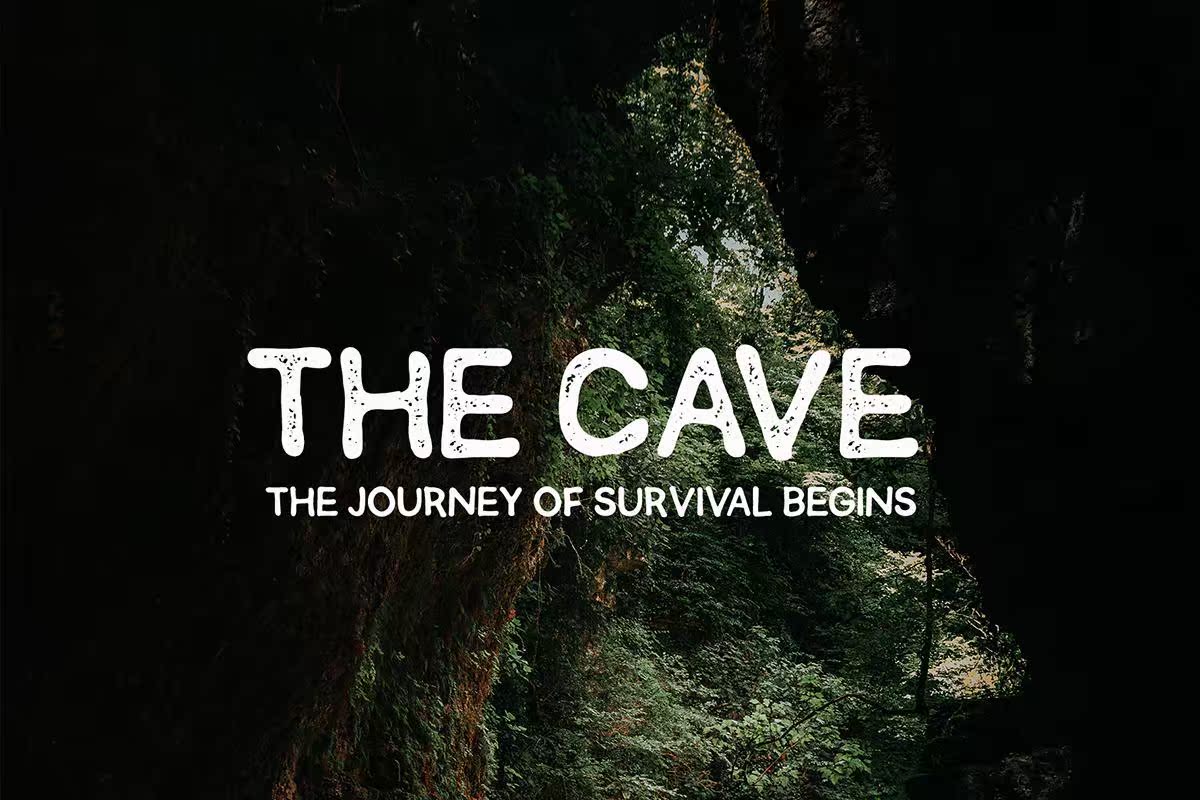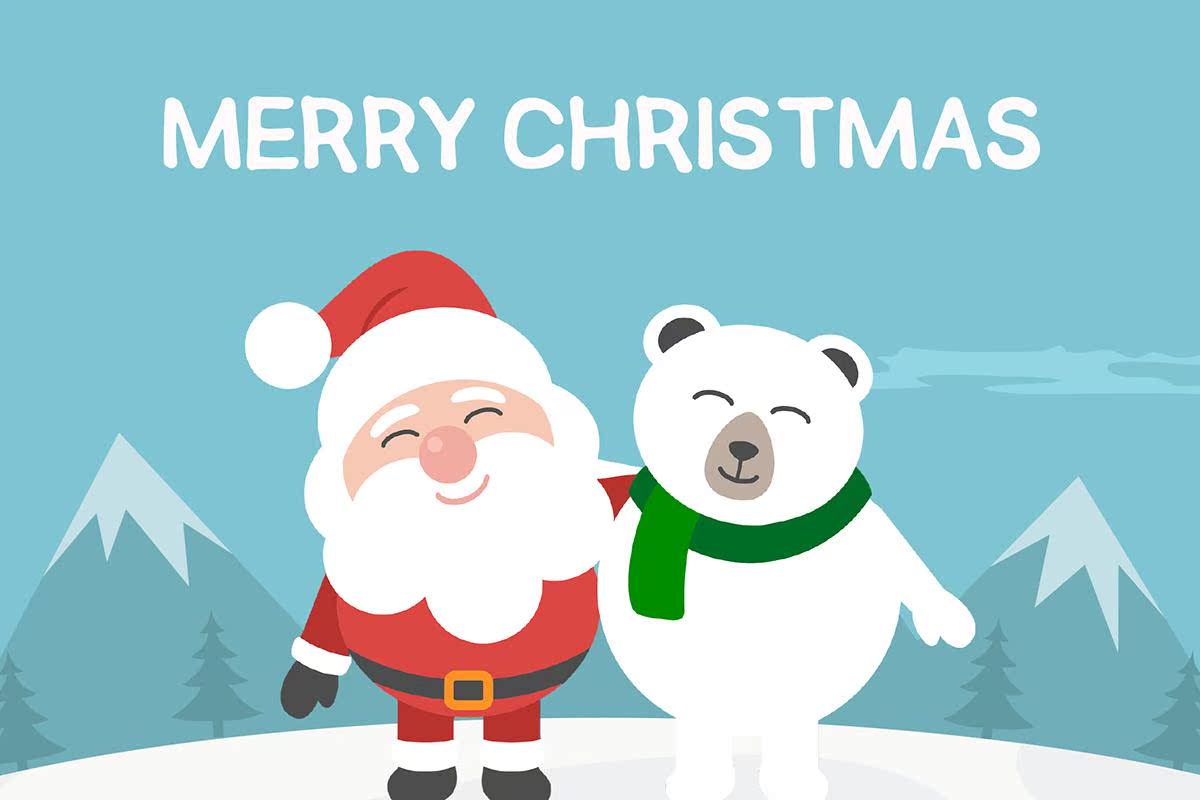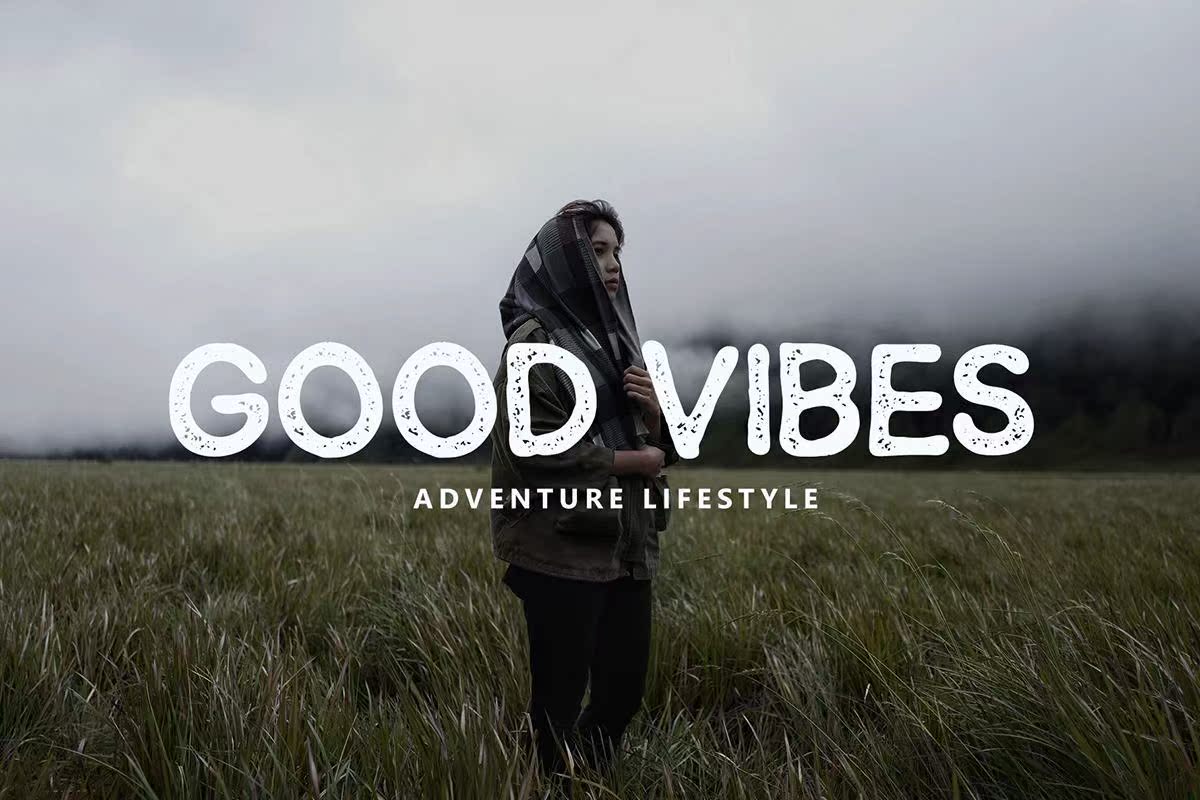
今天,我们获得了一个全新的freebiefont,它可以刷新和写入字体。它是一个供您在您的作品中使用的显示字体。此免费字体的功能是您可以将任何计算机安装到它。它适用于您的项目,包括商品、包装、T恤、杯子等。但是,此字体可供个人使用,但您需要获得更多功能,您可以在下面检查PremiumVersion。